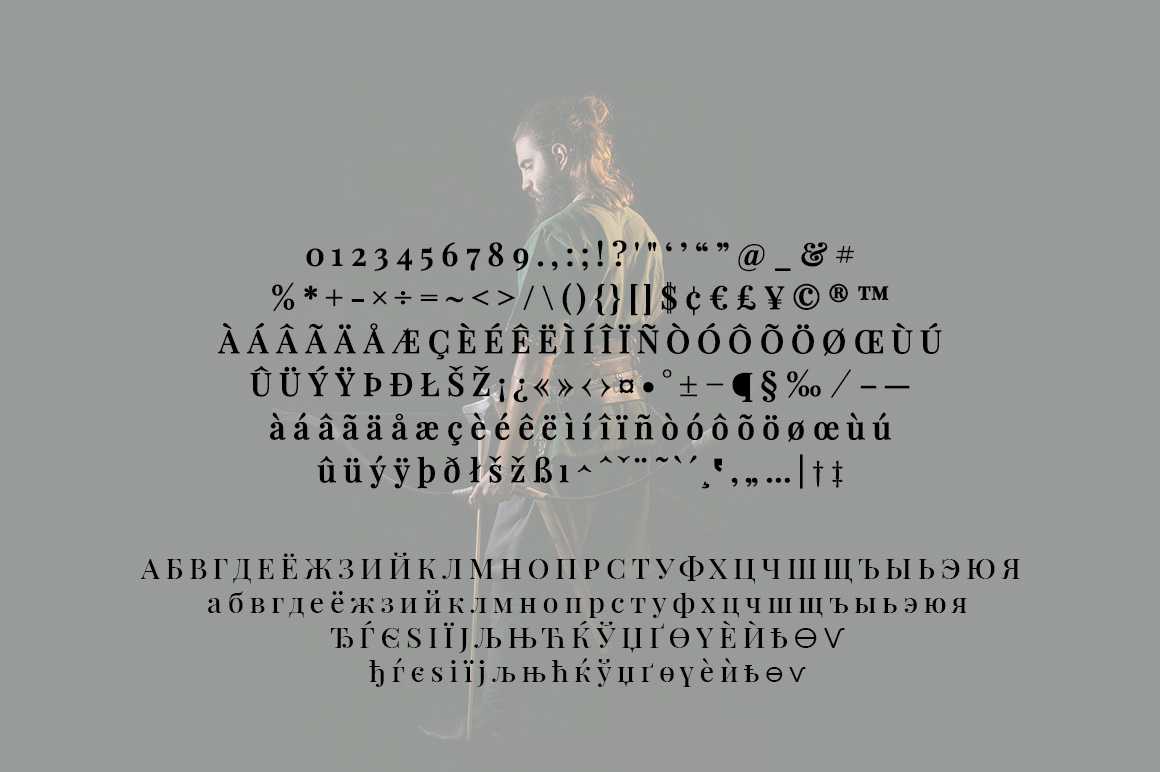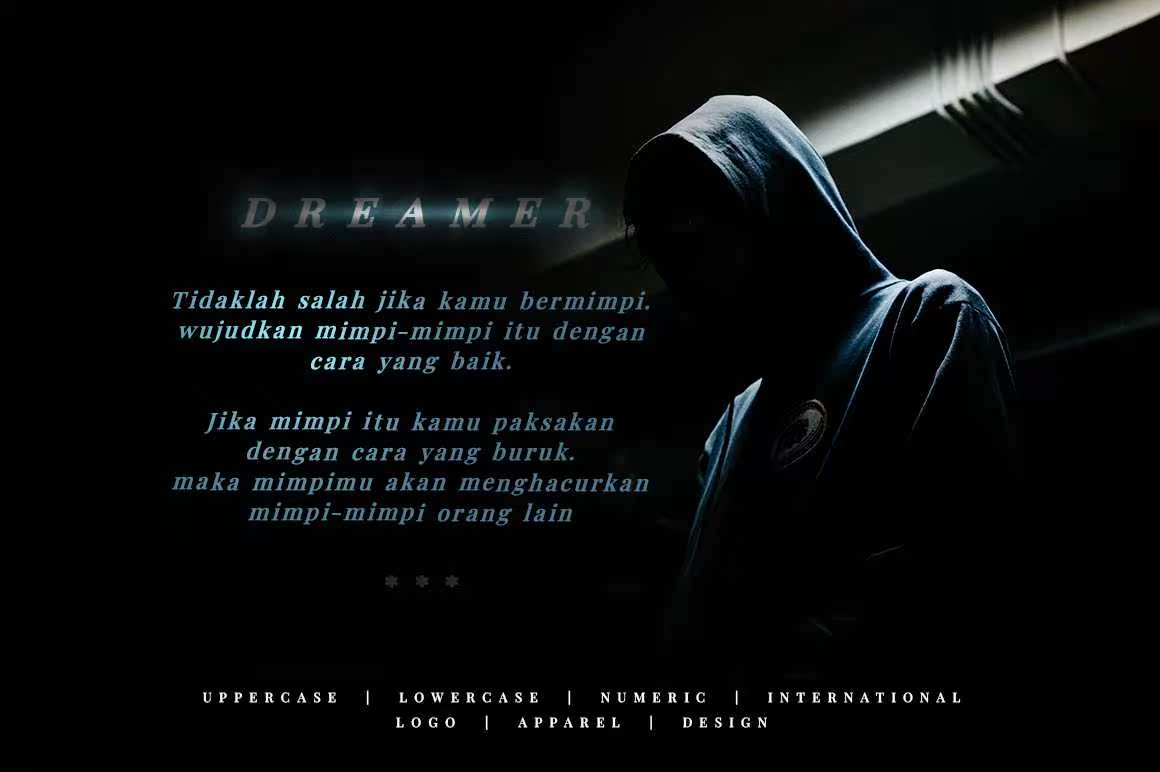
Garfieldfadefadmileyfontsangatcokokuntukposter,untuklogo,covermusik,pakaian,danbanyakbanyakproyekdesainkerainnya.Garfieldfadefadmileyfontalahhurufbesardanhurufkecil.fontnumerikdaninational.Reguler,Miring,tebaldanmiringtbabal.Garfieldfadefadefadmilefontsangatcokuntukuntuk,untakattakainn,untian,untuklogo,covermusik,pakaian,这是一个非常重要的项目。Garfield FadefamilyFontalahhurufbesardanhurufkecil。FontNumerikdani国际。调节器,调节器,调节器。